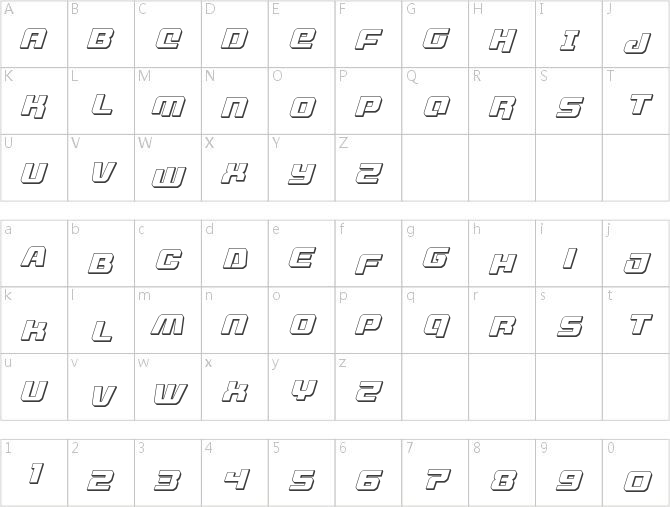
Livewired 3D Italic 詳情頁(yè)
Livewired 3D Italic字體字庫(kù)是一款讓人賞心悅目、百看不厭的英文字體,適合各類廣告和產(chǎn)品包裝設(shè)計(jì)應(yīng)用,字體大小0.04MB,格式為ttf字體,上傳用戶是一直在守護(hù),作者/版權(quán)方為未知